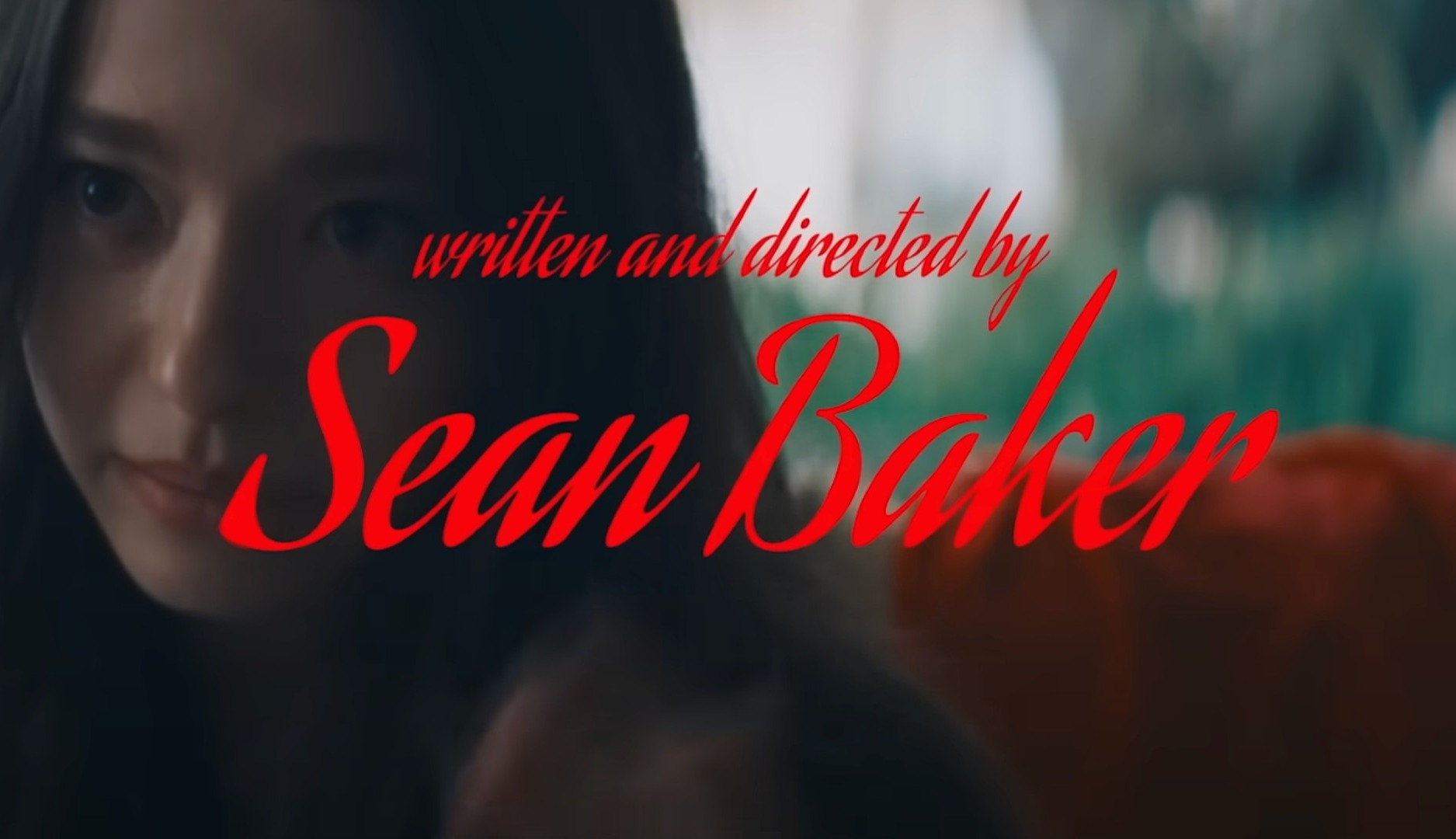
La tipografía es un elemento esencial en la identidad visual de marcas y productos de todo tipo, categorías e industrias. Y en el cine, donde todos y cada uno de los recursos empleados ayudan a construir una historia, cobra especial relevancia. El director Sean Baker, reciente ganador del premio Oscar a Mejor Dirección, parece ser consciente de ello y ha convertido la fuente Aguafina Script en un componente intrínseco de su estilo cinematográfico.
Baker ha convertido la tipografía, creada por los diseñadores Alejandro Paul y Ángel Koziupa de estudio argentino Sudtipos, en prácticamente una firma. Y es que la ha empleado desde el año 2015 en los créditos y carteles de todas películas, es decir, en los pósters de “Tangerine”, “The Florida Project”, “Red Rocket", y “Anora”, ganadora del Oscar a Mejor Película. De esta forma, la empleado en cuatro de las nueve películas que componen su filmografía.
El de Sean Baker no es el único caso de un director de cine engatusado por una tipografía concreta. Hay otros casos recientes que evidencian que el uso de una fuente puede convertirse en parte fundamental de la personalidad artística de un cineasta. Cabe mencionar, en este sentido, el uso de la fuente Albertus por John Carpenter en los créditos de películas como “Starman” o “Sobreviven”; y también es conocido el gusto de Stanley Kubrick y Wes Anderson por la tipografía Futura en sus diferentes versiones.
Baker sigue los pasos de Woody Allen que ha convertido la tipografía Windsor en un elemento unificador de su obra, especialmente a lo largo de las dos últimas décadas. La fuente, diseñada por Eleisha Pechey en 1905 para la fundición Stephenson Blake, es la escogida por el director para los títulos de crédito desde que en 1977 estrenara “Annie Hall”; y desde 2009, cuando presentó “Si la cosa funciona”, también ha protagonizado los carteles promocionales de sus cintas.
Es más, tal y como Baker trasladó en una entrevista para la plataforma Mubi, reconoce que el uso de una misma tipografía no es una idea original. “Me inspiré en John Carpenter y Woody Allen, sinceramente”, explicaba el director el pasado mes de octubre. “Ahora, cuando ves esas fuentes, piensas en esos cineastas y sus películas”.
Los casos de Allen y Baker son paradigmáticos, y en el caso del segundo, destacable ya que sus últimas cuatro películas, las que emplean la misma tipografía, han sido distribuidas por tres compañías diferentes. Sin embargo, tanto Magnolia, como A24 y Neon han respetado la preferencia del director por la fuente, quizá entendiendo el papel que el elemento visual juega en la construcción de su universo.
El estudio Sudtipos describe Aguafina Script como “grácil, pero no demasiado informal” y "artística, pero no demasiado imponente", lo que permite “una escritura muy atrevida”. Según cuenta Baker, la elección de esta tipografía se basó en la búsqueda de algo que fuera “estilísticamente interesante” para la escena de títulos iniciales de “Tangerine”, que tan sólo representaba las letras con una mesa amarilla de fondo.
También buscaba la contraposición. "Creo que fue una elección que también se hizo debido al tema, que supongo que se considera ‘áspero’, basado en la realidad, muy de nivel callejero", cometa Baker respecto a la fuente. “Quería ir en la dirección opuesta y trabajar con una tipografía que le añadiera elegancia, que evocara una sensación de sofisticación o capricho”.
Tras esto se dio cuenta que si continuaba empleando la fuente en el resto de sus películas, que también abordan cuestiones vinculadas a la realidad social, conseguiría una identificación entre el público y su cine. “Me gusta que haya coherencia entre mi material publicitario y los créditos reales”, apunta Baker, quien asegura que trabaja junto a los equipos de diseño de las distribuidoras para incorporar la fuente a la promoción.
Sean Baker, además, adelantaba que seguirá apostando por Aguafina Script en sus próximas películas. Con el uso de la misma fuente, el director no sólo desafía al espectador a no juzgar la historia por su apariencia, sino que otorga a este elemento visual la misma importancia que otros que componen su obra. La convierte en la bandera de su estilo.